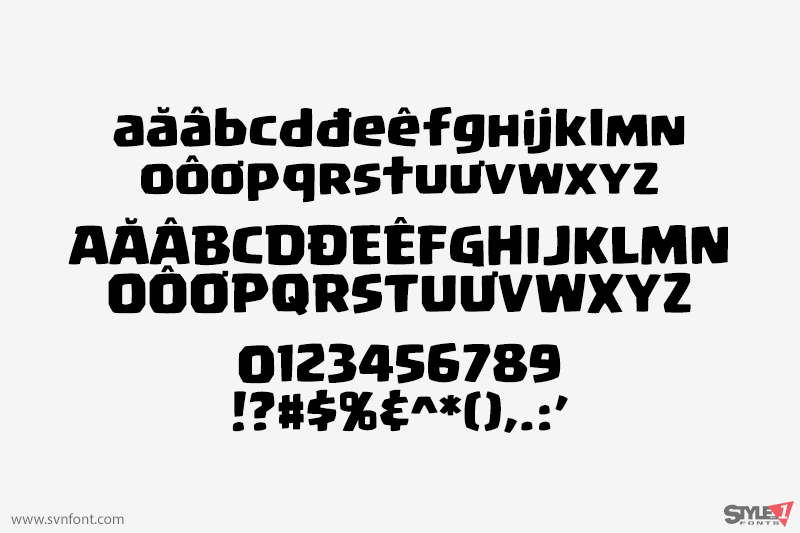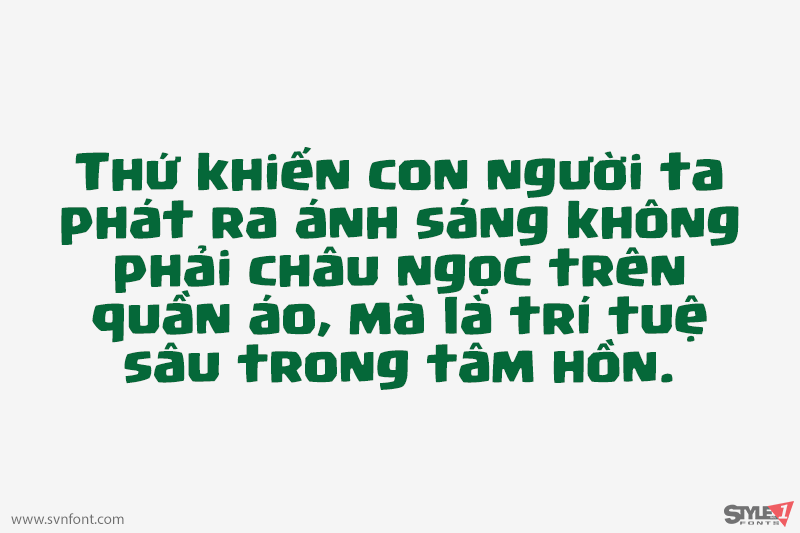
Font chữ Supercell Magic được sử dụng trong tựa game Clash Of Clans.
Nhà thiết kế: John ‘JG’ Roshell
Nhà phát hành: Active Images
Font chữ Supercell Magic được sử dụng trong tựa game Clash Of Clans.